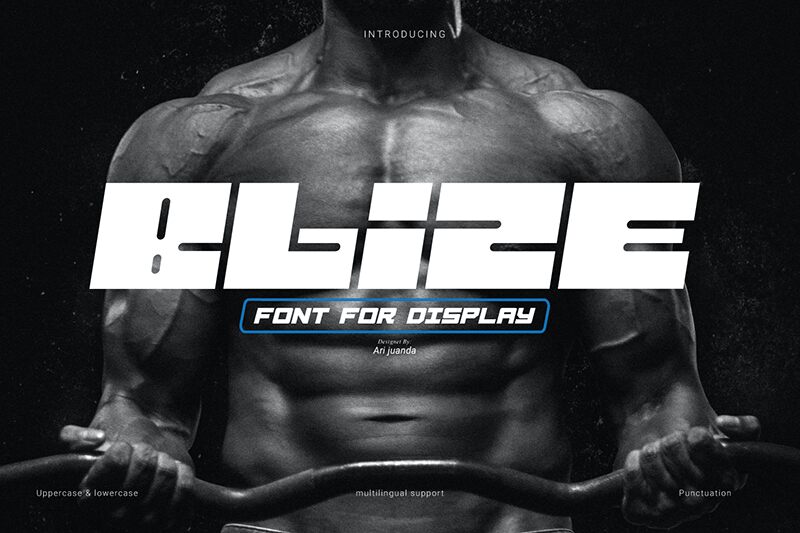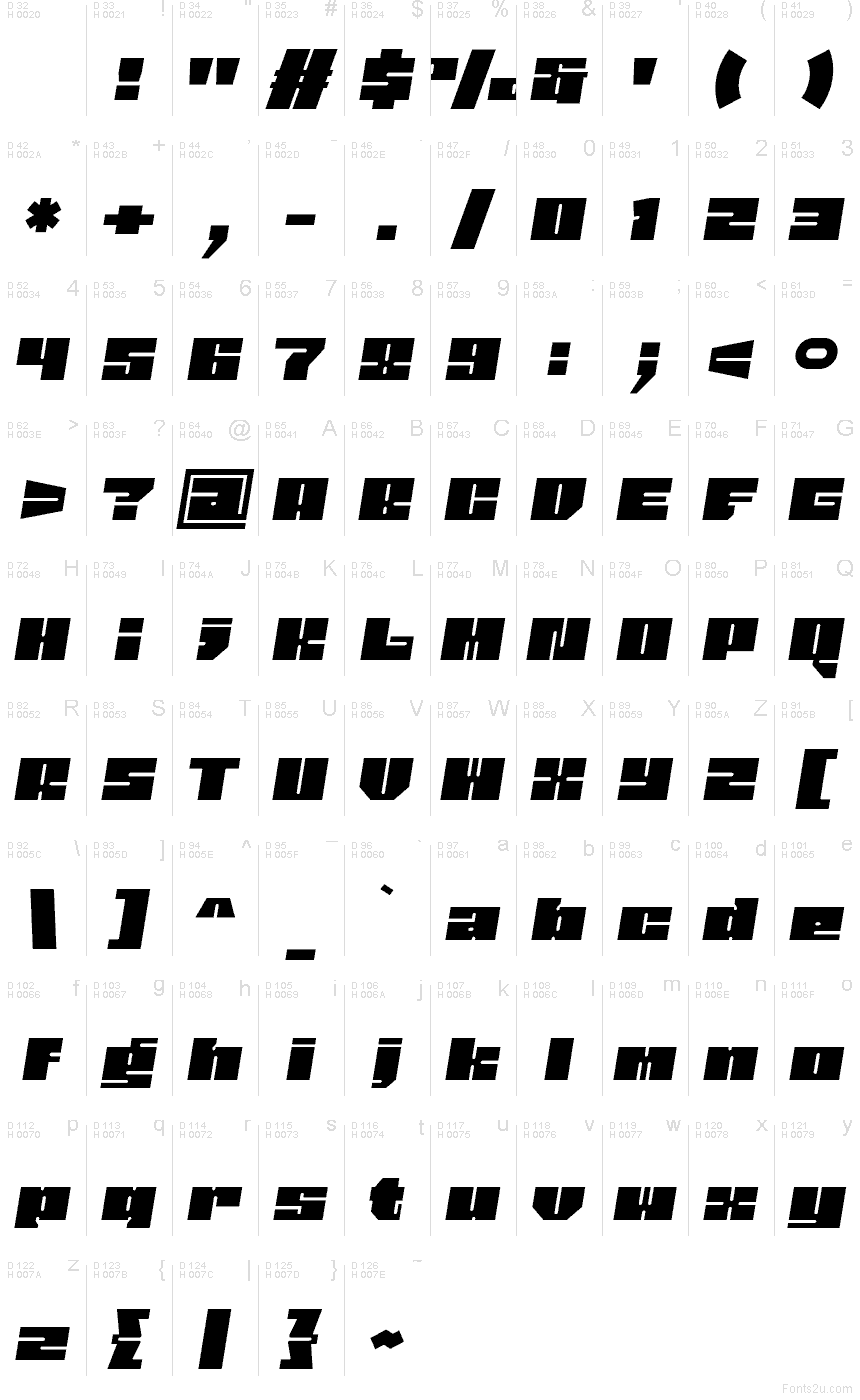
Blize di Linecreative è un carattere display futurista gratuito, realizzato con tratti sottili e rigorosamente progettati. Ampi spazi interni scompongono le lettere in sezioni modulari, ricordando pannelli di controllo illuminati e schemi tecnici. Le forme squadrate e le giunzioni nette mantengono la silhouette complessiva pulita e marcatamente meccanica.
Lo stile retrò-futurista lo rende ideale per poster di musica elettronica, interfacce di giochi arcade, brand tecnologici e grafica per eventi di fantascienza. Le forme ricordano percorsi di circuiti luminosi. Questo riferimento conquisterà soprattutto il pubblico attratto dalla cultura synth, dal gaming e dalle visioni vintage della tecnologia digitale.